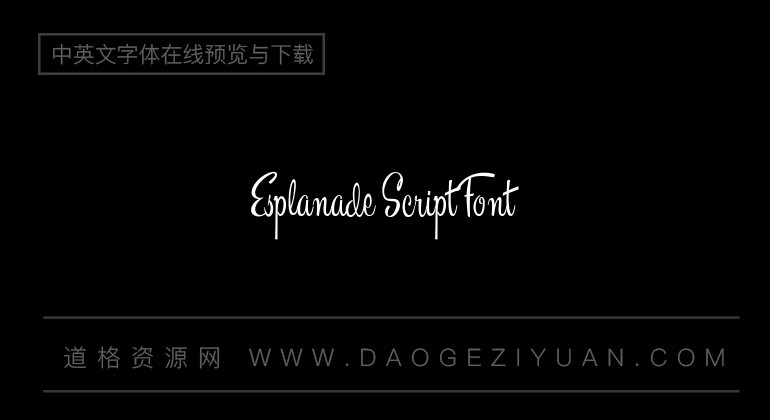
Esplanade Script Font 是一种优美的手写字体,具有非常自然、流畅的笔画和良好的可读性。这种字体的字母形状充满了细节和活力,使其成为很多设计师、文案小编以及创意人士的首选字体之一。 Esplanade Script Font 的特点在于它的笔画有粗细之分,这使得它看起来更加充满生命力。此外,它还有多种风格,包括斜体、粗体、常规体等,可以满足不同场景下的需要。 这种字体适合用于许多不同的设计领域,如文本设计、印刷设计、网站设计、标志设计等。如果你需要一种优美、富有个性和独特的字体,Esplanade Script Font 绝对是一个不错的选择。内容介绍
Esplanade Script Font是一款非常不错的手写艺术字体,具有很好的视觉感,适合于文化类的宣传设计、商业类品牌的广告和产品包装设计以及个性化文字排版等较多场景。